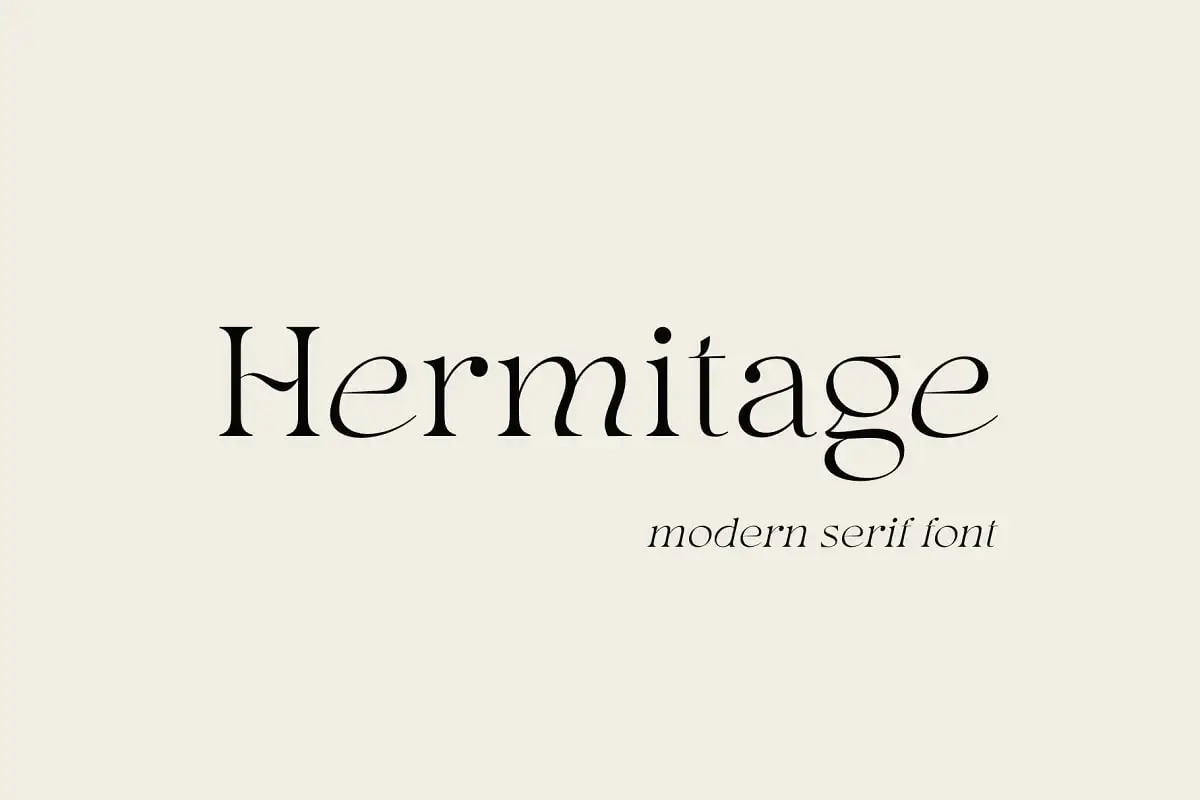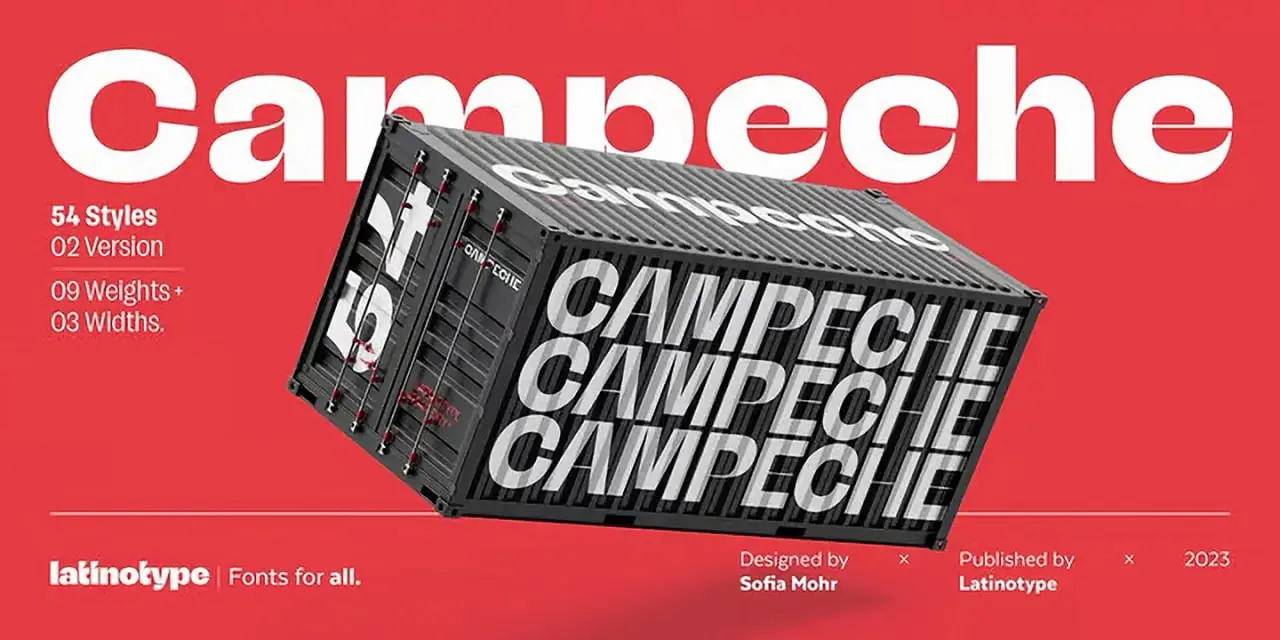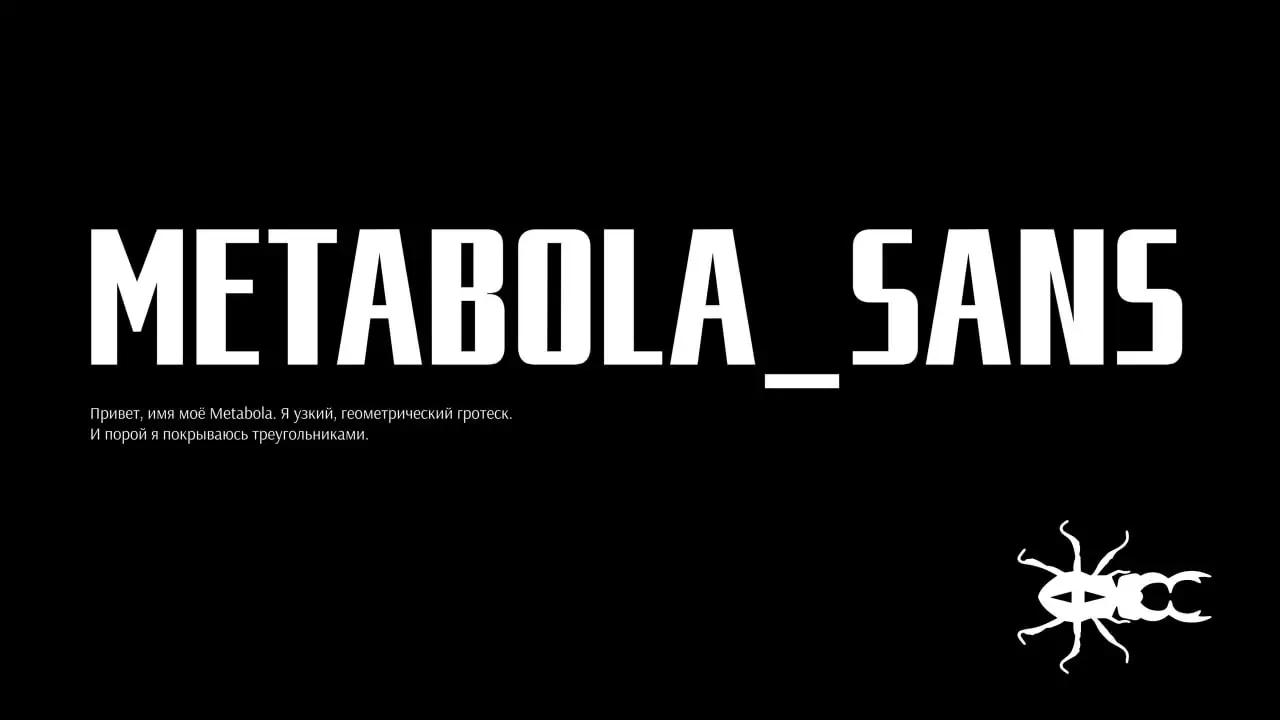
欢迎回来,充满创意的灵魂们!🎨✨ 我们无比激动地为你带来《第67期笔刷素材包》——一个装满20件令人惊艳的设计资源的巨大宝库。从优雅的衬线字体到俏皮的涂鸦风格,再到强大的Procreate笔刷,这个合集是你提升品牌设计、插画和数字杰作的终极工具箱。🚀
无论你是经验丰富的平面设计师、充满热情的数字艺术家,还是刚刚踏上创意之旅的新手,这些精心挑选的珍品都将为你的项目注入新的活力。别再等待,让我们一起探索第67期的魔力吧!🖌️💖
为什么要使用这些创意资源?
优秀的设计始于合适的工具。这些字体和画笔不仅仅是好看的皮囊——它们提供了多功能性、专业级品质和独特的美学,能将一个基本想法转变为视觉杰作。无论您需要粗体的标题字体、婚礼邀请函的精致手写字体,还是用于Procreate的粗糙纹理画笔,这个系列都能满足您的需求。🎯
精选20大创意资产推荐
Mogathe字体
认识Mogathe——优雅与现代感的完美融合!🌟 拥有多种字重和时尚的字形,这款字体将瞬间提升您的品牌和数字媒体设计。它干净、多功能,而且超级时尚!✨
Murahmaksa 日式灵感字体
用 Murahmaksa 释放传统日本书法的精神!🏯 这款字体拥有优雅的笔画和独特的设计,尽显艺术气息。非常适合为您的项目增添异域风情的手工质感。🖌️
Mephistophjimenez
准备好迎接一款为桌面带来极致现代风格的设计素材吧!🔥 Mephistophjimenez 拥有精致的细节和高质量的设计,使其成为品牌推广、营销和数字内容中的明星之选。独特而大胆!🎯
Middle Name 极简经典字体
简约从未如此迷人!😍 这款极简经典字体以干净的线条和永恒优雅著称。非常适合需要精致而不繁琐的标志、品牌设计和印刷物料。 🕊️
Melody 可变字体 — Boulevard Lab 出品
与排印的未来打个招呼吧!🎵 Melody 是一款可变字体,让您在不同字重和样式之间平滑过渡。超级百变,无比流畅——有了它,您的设计将如歌般优美!🎶✨
Mehmetrehatugcu-Azurite 字体
醒目而现代,Azurite 是一款引人注目的字体!💎 完美适用于品牌设计、网页设计和印刷,其清晰的线条和多种字重为您带来极大的灵活性。现代创意人士的必备之选!🚀
Metabola
Metabola 是一款兼具现代美学与强大功能的数字设计素材。🧬 易于自定义和集成,这款素材将为您的创意项目带来焕然一新的前沿视觉。准备好开始实验吧!🎨
Maulana Creative-Machinkly 展示字体
用Machinkly做出醒目宣言!🚀 这款展示字体创意十足,在众多字体中脱颖而出。非常适合海报、标志和促销宣传,既能保证高可读性,又能彰显鲜明个性。🔥
现代字体
有时你只需要一款能直呼“当下”的字体。现代字体干净利落、时尚前卫,在品牌设计、用户界面和印刷作品中都非常灵活。🖥️ 它是经典的全能型字体,兼具现代感!✨
Mister Brush
全体Procreate爱好者请注意!🖌️ Mister Brush 是一款多功能的笔刷合集,包含墨线、绘画和纹理笔刷。无论您是专业人士还是爱好者,这些笔刷都能以丰富的纹理和效果,让您的数字艺术栩栩如生。🌟
Magison Tech Sans By Typia Nesia
懂技术的设计师们,这款字体为你们而生!🤖 Magison Tech Sans 将简洁线条与现代美学融为一体,非常适合品牌设计、用户界面和网页设计。无论尺寸大小,都清晰易读!📱
Larin Type Co.-Hermitage
Hermitage 诠释优雅真谛!🌹 这款精致字体拥有优美曲线与干净利落的线条,为现代品牌和高阶项目带来惊艳效果。尽显高端气质!👑
Lewis Mcguffie-Tusker Grotesk 完整字体系列
这套完整的字体家族是现代品牌的强力助手!💪 Tusker Grotesk 提供从标志到网页设计的多种字重和风格,干净、有力且极具通用性。🏆
Kelsi Free 涂鸦气泡风格字体
把街头艺术带到你的屏幕上!🎨 Kelsi 是一款有趣、俏皮的涂鸦泡泡字体,充满活力。非常适合海报、贴纸以及任何需要狂野都市氛围的设计。个人使用完全免费!🆓🔥
Letov By Serg Shishin
优雅与现代在 Letov 中碰撞!✨ 这款精心设计的字体非常适合品牌设计、标志和网页应用。拥有多种字重和广泛的语言支持,既实用又美观。🌍
Kajiro Sans Condensed Display — 由 Maulana Creative 设计
节省空间又时尚!📏 Kajiro Sans Condensed Display 是每个像素都很重要的标题的理想选择。其简洁、现代的美学风格,使其成为品牌推广和宣传材料的首选。🏷️
Lethal Craze Font By Thebrandedquotes
前卫、大胆,简直致命!💀 这款由Thebrandedquotes设计的字体拥有独特的字形,彰显现代动感。非常适合吸引眼球的大标题和需要态度爆棚的项目。🚀
Latinotype-Campeche 字体系列(Sofia Mohr 设计)
Campeche 是一款惊艳的衬线字体系列,为任何项目带来经典优雅。🌸 它包含常规、粗体和斜体样式,在印刷和数字媒体中都非常灵活。你的设计将看起来价值连城!💰✨
Margo Medium Condensed V0
当空间有限但冲击力至关重要时,Margo Medium Condensed 就是你的救星!🦸♂️ 这款中等粗细的紧缩字体非常适合需要在不牺牲风格的前提下脱颖而出的标题、标志和用户界面。💥
Kallisoka 现代优雅衬线字体
最后但同样重要的是——认识一下Kallisoka!🌹这款现代优雅衬线字体将当代设计与经典格调完美融合。非常适合需要彰显高级魅力的品牌标识、标志设计和印刷物料。🕊️✨
总结
各位,以上就是Brushespack系列第67期的完整阵容!🎉从优雅衬线字体到涂鸦字体,再到多功能的Procreate笔刷,这个系列堪称每一位创意灵魂的宝藏。每款素材都旨在激发灵感、提升品质,将您的项目蜕变为非凡之作。🚀
常见问题解答
什么是 Brushespack 系列第 67 部分?
Brushespack 系列第 67 部分是一套精心策划的 20 款优质数字设计资源,包括现代字体、字型和 Procreate 画笔。它非常适合追求高品质创意工具的平面设计师、数字艺术家和品牌专业人士。